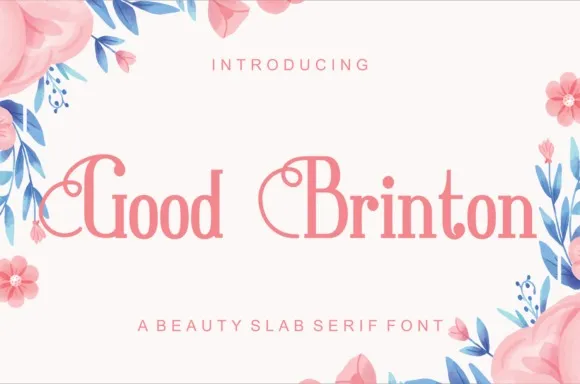
A fonte Good Brinton é uma combinação perfeita de elegância clássica e versatilidade. Manufacturada pela LetterBeary, ela se destaca como um tipo serif que é tanto ideal para grandes projetos quanto pequenos detalhes. Seu uso variado pode incluir cabeçalhos, logotipos, rótulos, projetos de marca, revistas, designs de mobiliário, embalagens de produtos, chávenas, citações, postais e muito mais. O que torna essa fonte tão interessante é sua capacidade para expressar tanto a seriedade quanto o humor. Com seus muitos alternativos e binder’s, Good Brinton oferece uma gama rica de opções, tornando-a ainda mais versátil e atraente. Se você está buscando um tipo que pode adaptar-se a qualquer projeto, esta é sua fonte perfeita. Categoria: Serif Fonts Designer: 99designs